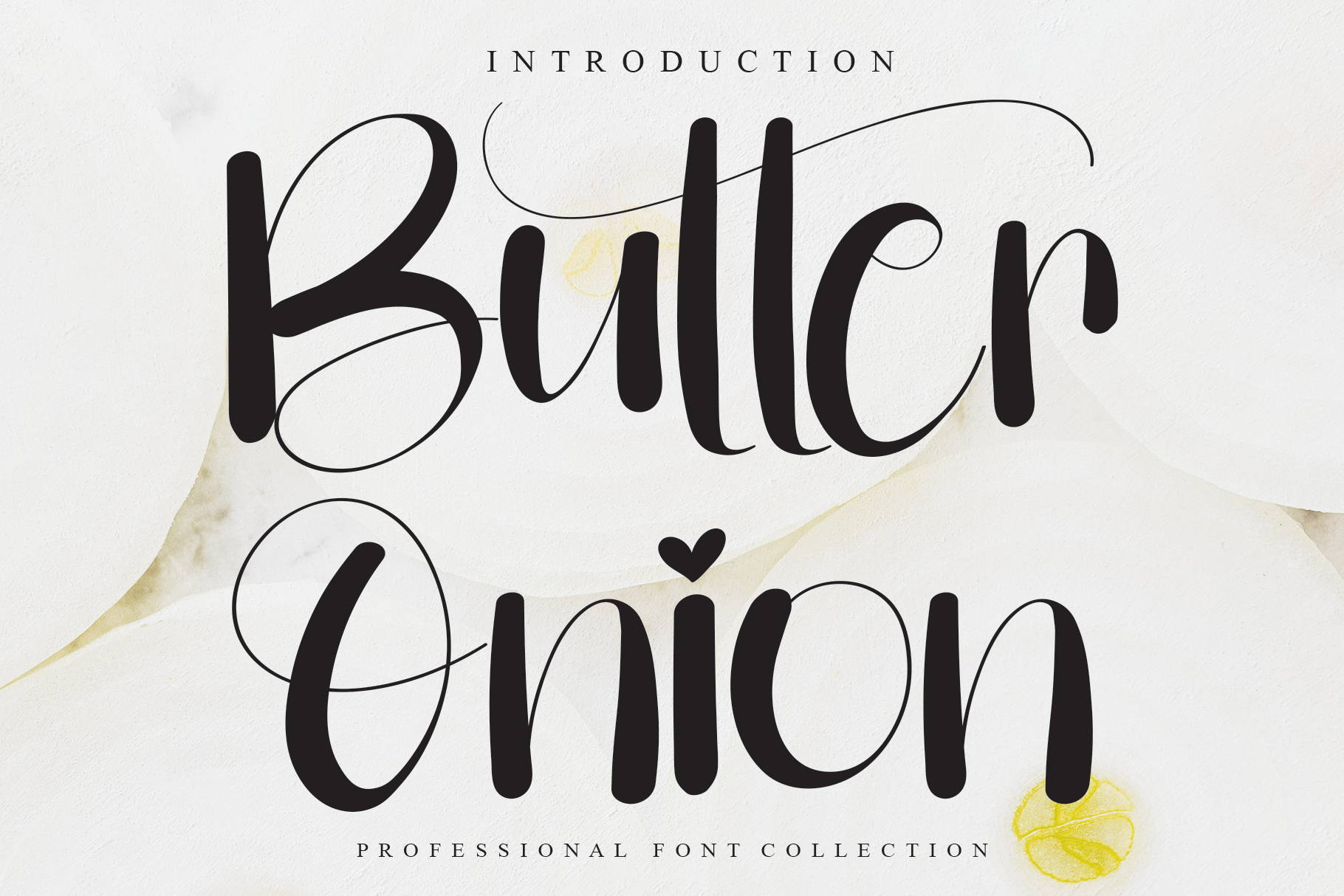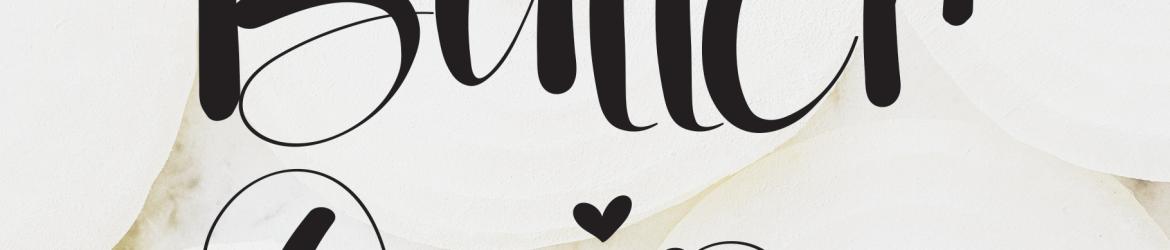
Butter Onion Font – Download Grátis
Esta é uma bela e delicada tipografia feita à mão que transmite elegância e classe. Foi especialmente criada para aqueles que buscam um visual encantador e renovador em seus trabalhos de design. Com sua estrutura fluida e movimento suave, a Butter Onion Font proporcionará um toque especial às suas criações. Este é o tipo certo para adicionar um toque único e sofisticado ao seu próximo projeto, tornando-o imediatamente chamativo e impecável em qualquer layout ou página de design. Engane-se se pensa que a Butter Onion Font só serve para escrever; ela pode ser usada tanto para fontes quanto para títulos, garantindo sempre um resultado elegante e fresco.